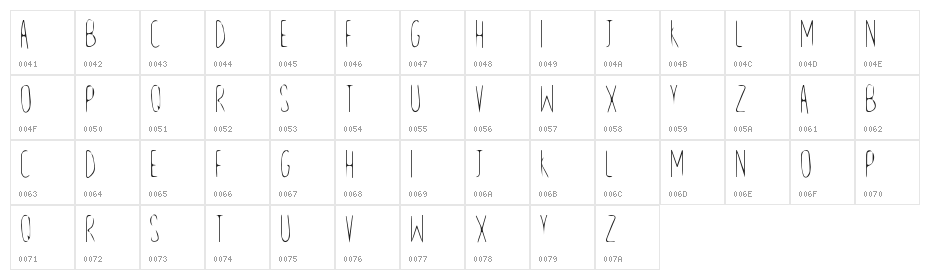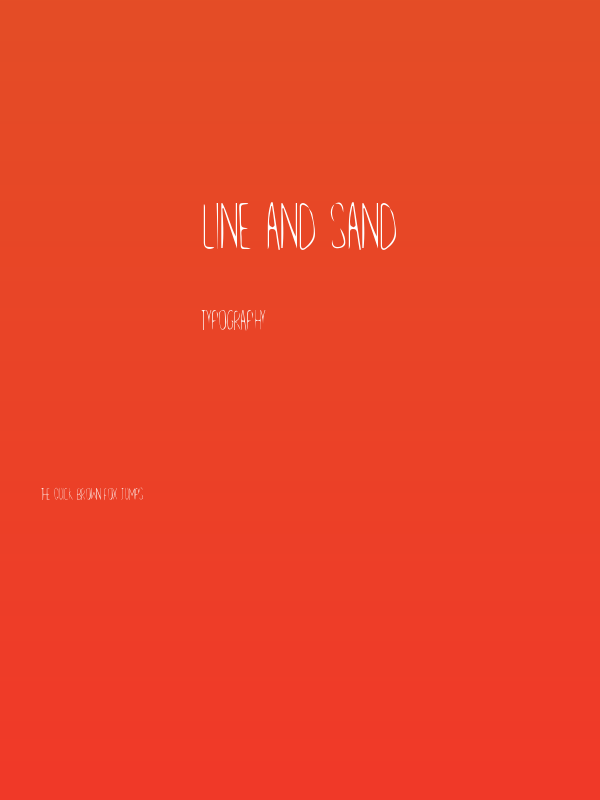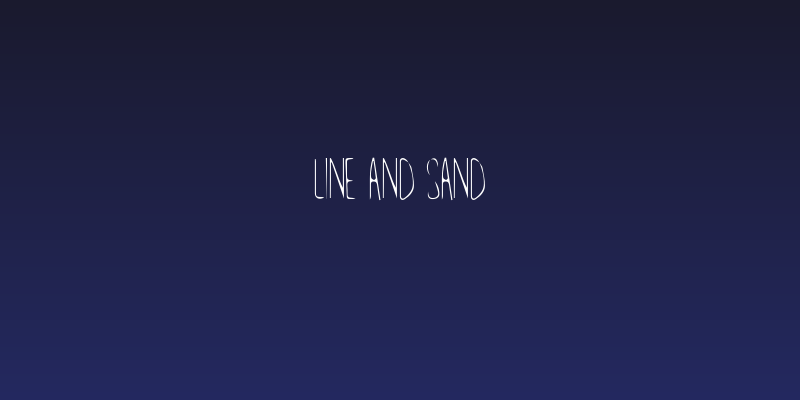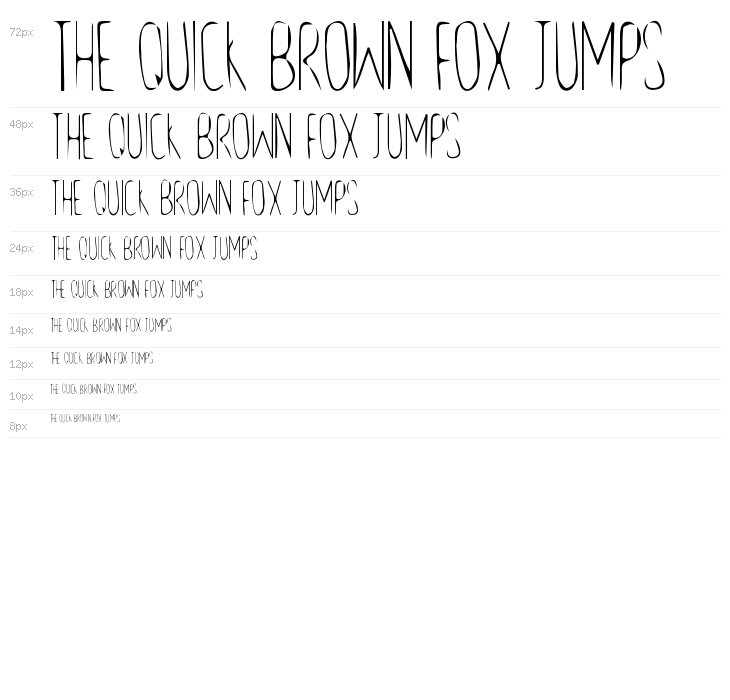
Line and Sand Font
✎ Handwritten
Fonts by Sarah Morris
| 分类 | Handwritten |
| 宽度 | Condensed |
| 整体风格 | Modern, Elegant |
| 使用场景 | Headlines, Logos, Branding |
| 推荐项目 | Ideal for fashion magazines, luxury branding, modern art posters, and minimalist web design. |